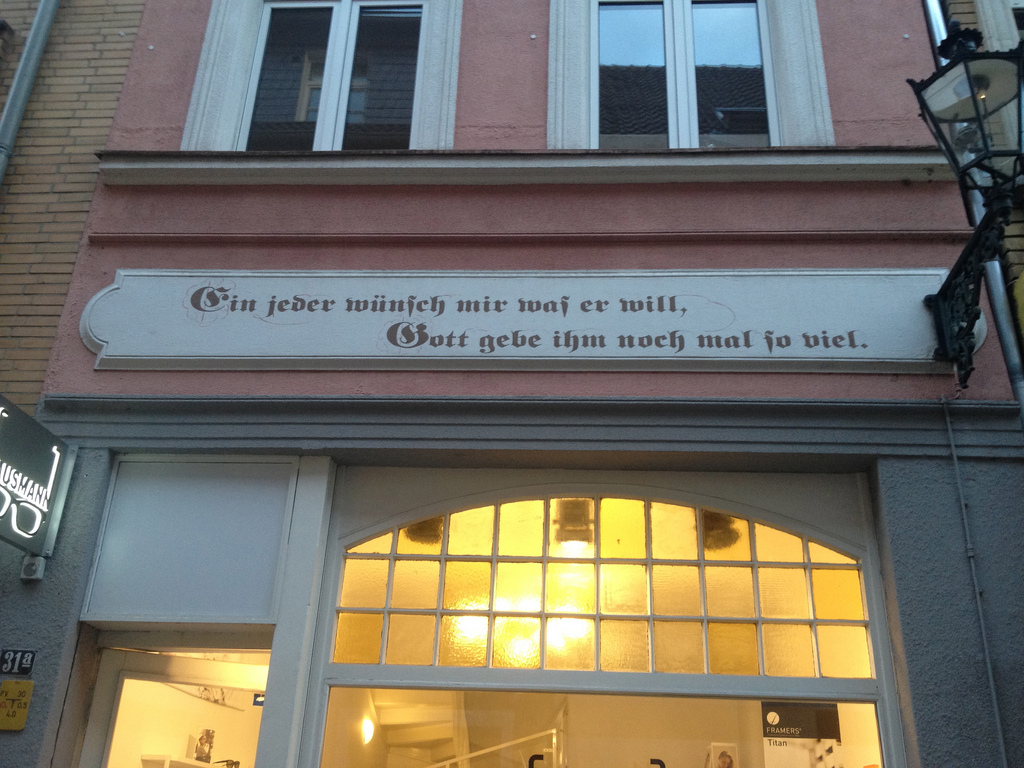
Neue Rechtschreibung?
Doch, denn habe ich da ein ganzes Sortiment von Hundshaufen, kann ich schon davon ausgehen, dass dieses Arangement insgesammt von mehreren Hunden dort platziert wurde
Dann sind wir jetzt beim Semmelknödel-Problem angelangt.
Hier ist es ja gerade anders herum, denn kaumn wird genau ein Knödel aus genau einer Semmel gefertigt.
Aber zurück zu den Haufen: Auch das kann ja durchaus sein, dass in Einzelfällen ein Haufen dadurch, dass ein 2. Hund seinen Anteil auf einen schon vorhandenen Haufen hinzugefügt hat eben ein Haufen sein, der letztlich in zeitlicher Abfolge von 2 odere mehreren Hunden zu einem größeren Haufen zusammengefüht wurde.
Somit ist unter Hunde(mehrzahl)-Haufen(mehtzahl) eben alles möglich: Mehrere Haufen eines Hundes an mehreren Tagen, Mehrere Haufen, von denen einzelne dabei sind, an denen zufällig mehrere Hunde beteiligt sind, sowie viele Haufen in jeweils Einzelfertigung.
Ne, das macht nur der Teufel ...
Bei Hunden habe ich das in 20-jähriger Hundehalterschaft noch nicht gesehen, das ein Hund auf den Haufen eines anderen kackt – und ich habe da schon vieles gesehen ... :blabla::-o
Was ist denn 2D Vol(l)umenthumorgraphie??
Das hat irgendwas mit Humor zu tun, oder …?  ☺️
Nach neuer Rechtschreibung bitte mit drei l und zwei m auch zwischen Vokalen!
Volllummen sind halt zu tief ins Glas geflattert, diese Trottellummen ...
Oder geht's doch um voll krasse Volllumen-Taschenlampen?
Habe ich in einem anderen Forum verlinkt, aber wohl selbst nur flüchtig gelesen, so dass erst jemand anderes den Tippunfall bemerkte:
Das erreichen wir, indem wir ... die Möglichkeit ... zur Anordnung von Überholverboten von Radfahrerenden ... einführen.
Ist ja auch logisch, in Höhe von Radfahreranfängen käme ein Überholverbot auch zu spät ... *seufz* ;-)
Zu Risiken und Nebenwirkungen von Genderenden ...
.. Redakteure offensichtlich auch nicht.
Zumal das mit Kommas noch eine Aussage auf Gegenseitigkeit ist, ich schreibe mal statt allarmieren das Wort beklagen:
Professoren beklagen, Studenten könnn nicht mehr richtig schreiben.
aber auch:
Professoren, beklagen Studenten,  könnn nicht mehr richtig schreiben.
Da komme ich doch gerade auf die Idee, dass man die Lesbarkeit auch kommafrei verbessern könnte, würde man mit Bindestrichen die Verben mit den zugehörigen Substantiven verbinden:
Professoren-beklagen Studenten-könn'n nicht mehr richtig schreiben
Professoren- beklagen-Studenten -könn'n nicht mehr richtig schreiben.
Hmmm ... Ist zwar kommafrei, aber komafrei wohl gewöhnungsbedürftig ... ;-)
Aber ganz ohne Satzzeichen ist die Aussage schon sehr doppeldeutig - aber das kann ja durchaus auch richtig sein, denn es entspricht ja auch der Sichtweise der beiden Gruppen. In meinem Studium haben wir Studenten oft die muiserablie Schrift und auch Rechtschreibung an der Tafel oder später zusätzlich und gleichzeitig auf Beamer... Ach ne, Overhead-Folien bemängelt. Das ging dann oft nur im Team, einer schreibt die Tafel mit, der zweite die  schreibt die Beamer-Folien ab, und der dritte das gesprochene Wort...
Und in den Klausuren bemängelten dann die Profs unser unleserliches und oft in der Rechtschreibung wenig perfektes Geschreibsel...
... ...Gott gebe ihm noch mal so viel!
Ähnelt sehr dem was mein Vater über seiner Werkstatt- Tür aufgehängt hatte :
"Allen die mich kennen,
gebe Gott,
was sie mir gönnen."
Hatte er in Fraktur in Holz geschnitten.
Nur ein paar unzusammenhängende Gedanken zum Thema Fraktur/Antiqua
Zuerst eine kleine Anekdote ... heute in der Bibliothek erlebt.
Eine Gruppe von Schülern ... konfrontiert mit einem Zeitungsausschnitt aus den 20er Jahren de 20. Jahrhunderts ... in Fraktur ...
Wirklich original.
"können Sie uns das übersetzen"
"das ist deutsch"
"nein ... das kann doch keiner lesen"
Die glaubten das erst, als ich ihnen das vorlas. Aber sie konnten mit Fraktur nichts anfangen. Das war ihnen so fremd wie kyrillische oder griechische Schrift, möglicherweise noch fremder.
Ich denke damit ist jegliche Frage der Lesbarkeit von Fraktur erledigt. Fraktur ist ein Schriftsystem, das heute so obsolet ist wie Kirchenslawisch oder Runen, nur noch für Wissenschaftler interessant.
Nicht dass ich nicht auch gerne Texte in Fraktur  lese. Aber Fraktur hat sicher nichts - und auch wirklich nichts mit der Entwicklung der Schriftsprache zu tun. So wurden z.B. alle deutschen Texte in Drucken vor ca 1474 in Gotico-Antiqua gedruckt, einer Schriftart mit Antiquaminuskeln  und moderaten gebrochenen Majuskeln. Und wenn man etwas weiter zurückgeht, zum Beispiel fast alle älteren deutschen Schriftdokumente bis ins 14. Jahrhundert sind in von der karolingischen Minuskel abgeleiteten Formen geschrieben, nicht in gebrochenen Formen.
Ganz offensichtlich  hat das auch mit dem Alter - oder hier besser - der Jugend zu tun.
Was in den Schulen nicht mehr gelehrt wird, wird einfach als "nicht Deutsch"  bezeichnet.   Daß ich die Fraktur in  unterschiedlichen  Ausführungen kennen
und schätzen gelernt habe,  verdanke ich einem  Freund unserer Familie. Ein
Oberstudienrat, der auch Deutsch unterrichtete,  und der Meinung war, daß
ich unbedingt  dies Kulturgut kennenlernen müsste.  Er hat mir dann erst
"Jörn Uhl " und später auch "Die Ahnen" in Fraktur zu lesen gegeben. Das Prägt!